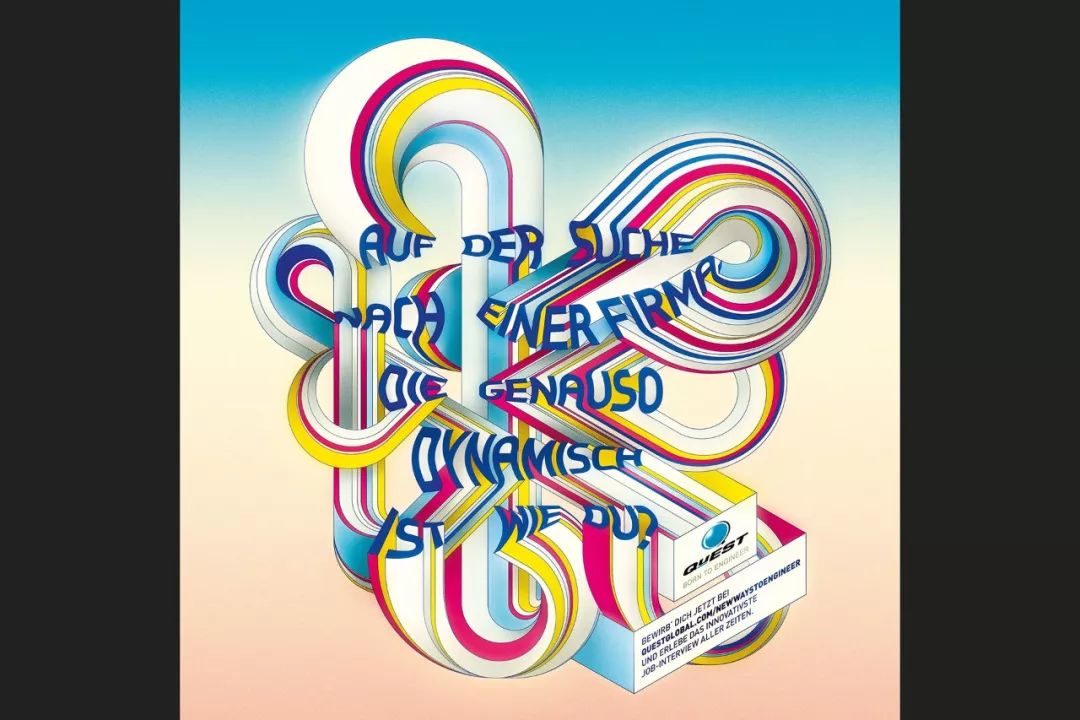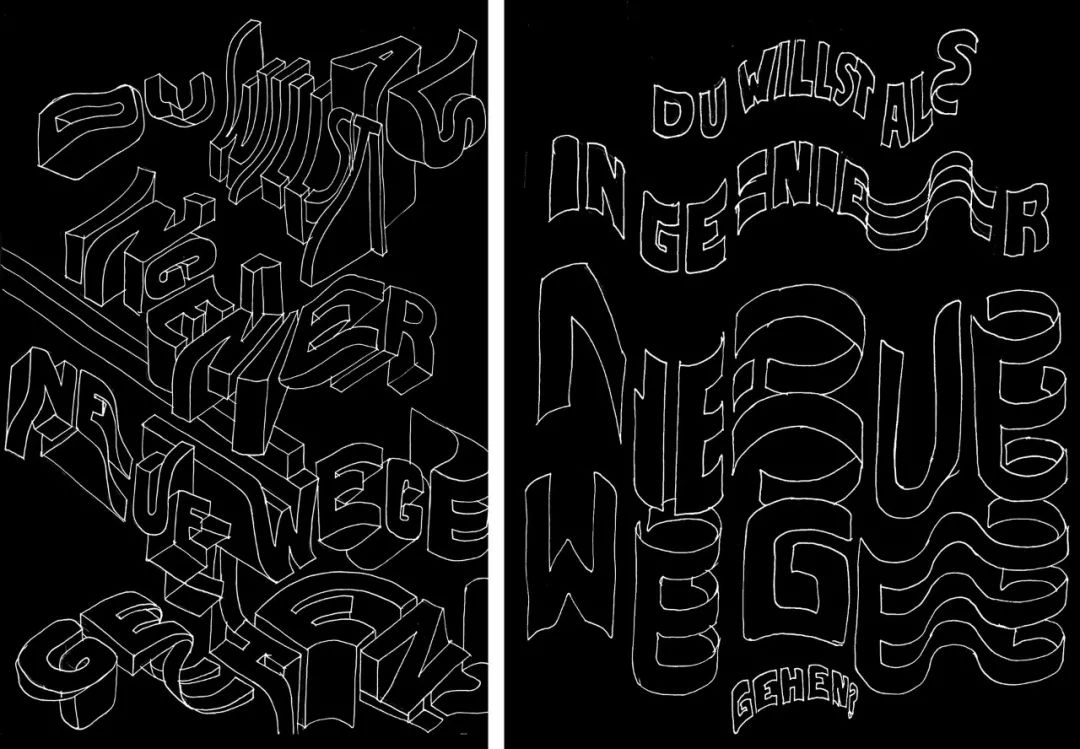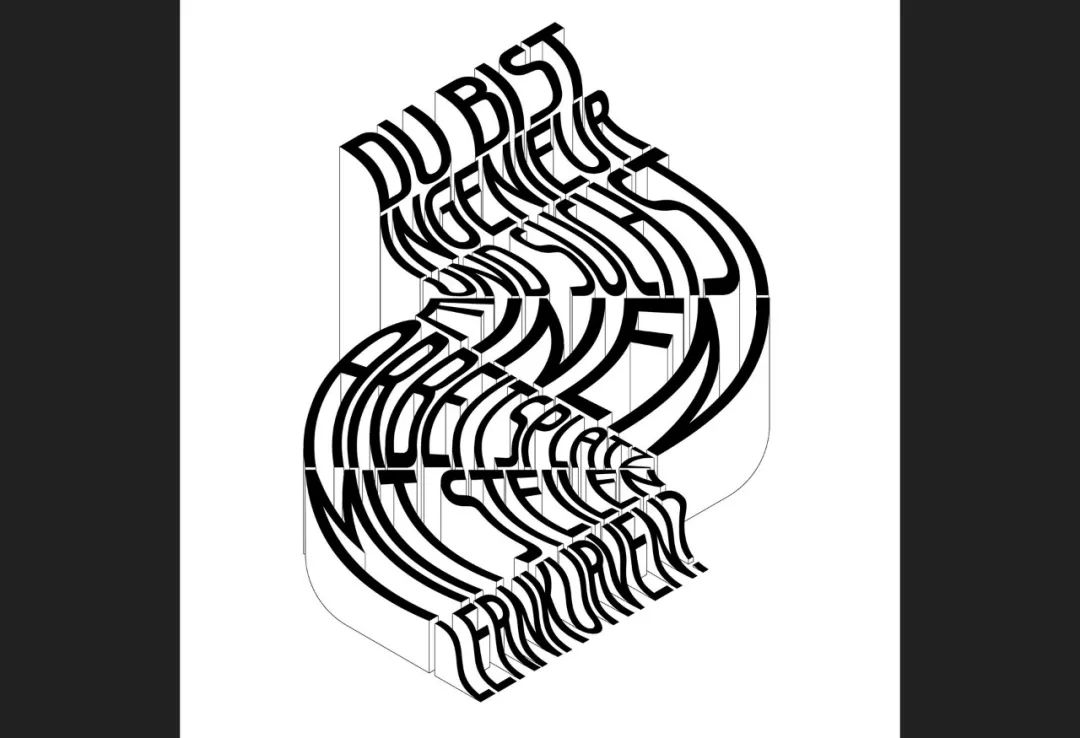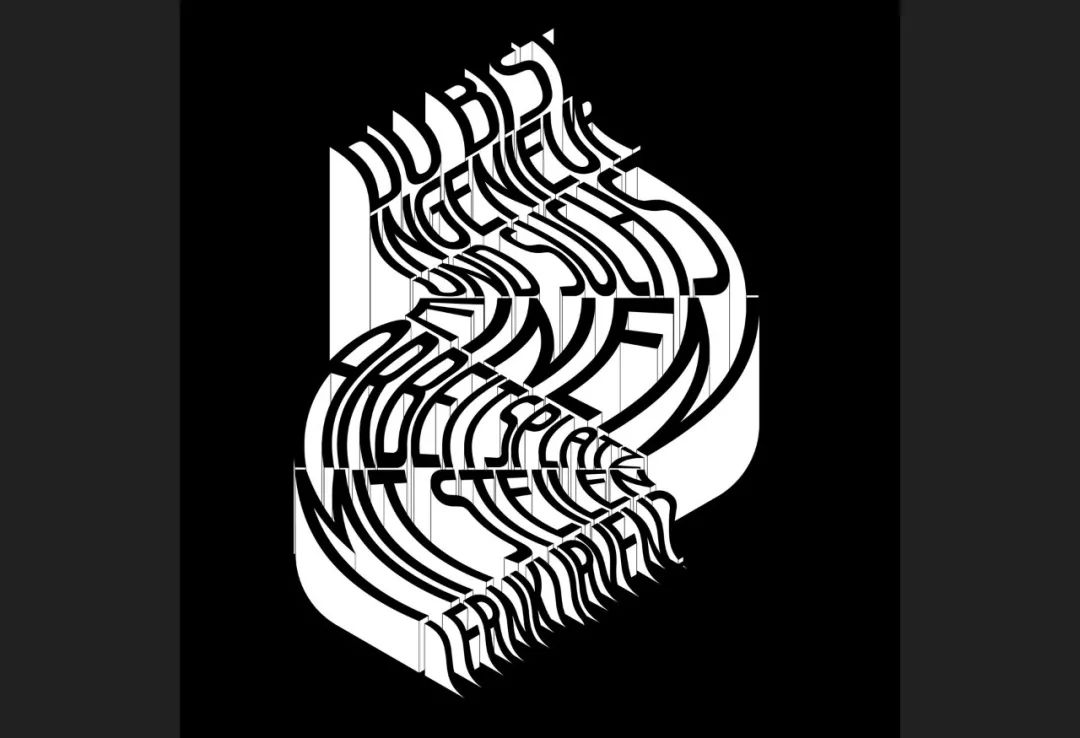
使用有趣的立体字来实现动态的排版艺术
英国设计师 Made Up 被委托制作一系列海报来宣传 Quest Global 。目的是设计出动态的排版艺术作品,以有趣的方式立体字体来表现。
作为设计师,一个很大的挑战是理解语言结构,使视觉强调工作正常。总之,这是一个令人着迷的项目。一起来看看设计过程。
“DO YOU WANT TO WORK FOR A COMPANY THAT'S AS DYNAMIC AS YOU?”
“DO YOU WANT TO WORK FOR A COMPANY WITH A TRULY FLAT HIERARCHY?”
“DO YOU WANT TO ENGINEER IN NEW WAYS?”
“DO YOU WANT TO TURN YOUR ENGINEERING CAREER UPSIDE DOWN?”
“DO YOU DARE TO GIVE YOUR ENGINEERING CAREER A NEW DIRECTION?”
“ARE YOU AN ENGINEER LOOKING FOR A JOB WITH A STEEP LEARNING CURVE?”